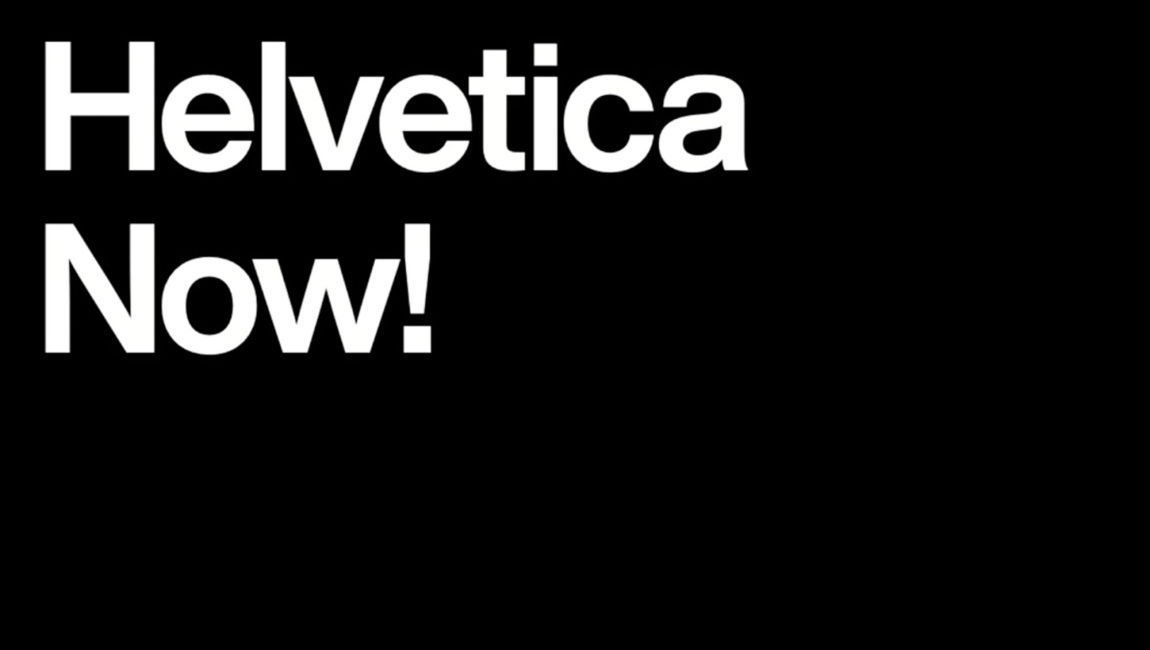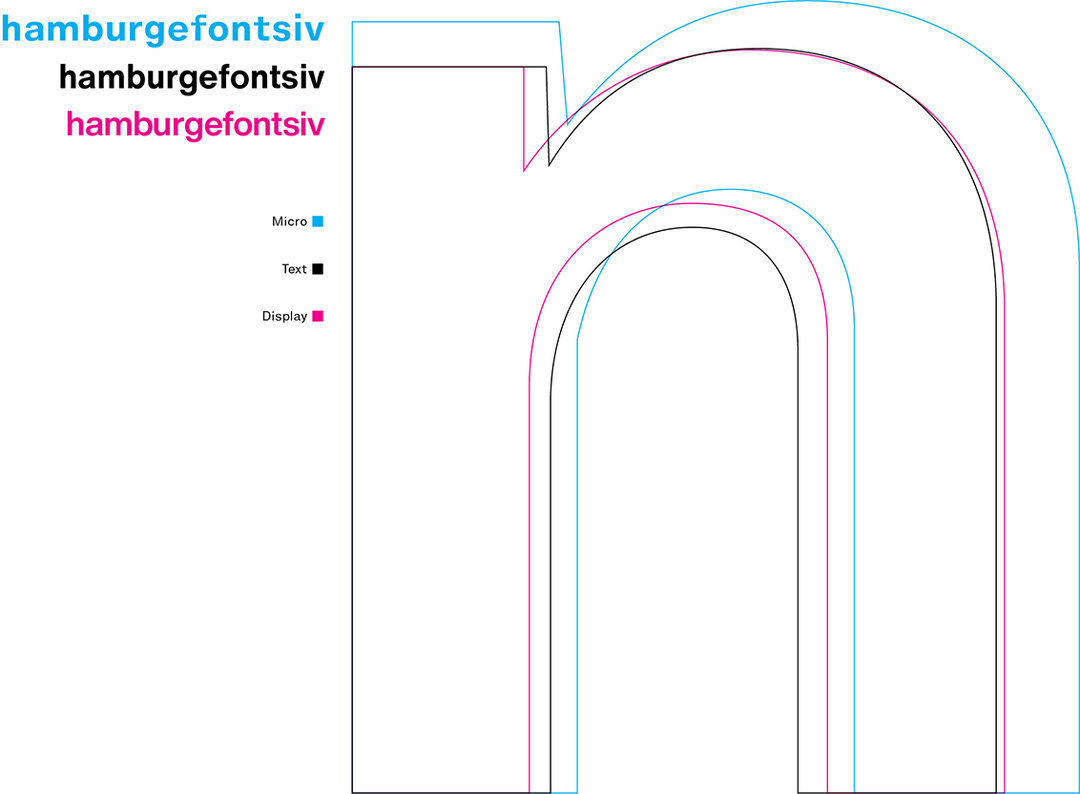
为了让经典的 Helvetica 字体更加适应当今时代,Monotype 公司经过多年的努力,终于在 Helvetica Neue 推出 35 年之后再次对 Helvetica 字体进行了更新,近日发布了全新版本的 Helvetica Now 字体。
Monotype 公司在声明中提到「Helvetica Now 是有史以来最著名字体的故事的新篇章。它提供了三种光学尺寸——微型、文本和显示。Helvetica Now 中的每个字符都经过重绘和重修,提供了更多种的选择。它拥有我们所喜爱的 Helvetica 字体的全部元素以及我们如今排版所需的一切。」
Helvetica 字体诞生于 1957 年,因便于识别、简单易读而被广泛采用并风靡全球。为适应时代需求,该字体于 1983 年经过重新设计后成为 Helvetica Neue 字体并延续至今。
苹果多年来一直也是 Helvetica 字体的拥护者,比如 iPhone 从初代开始就已将 Helvetica Neue 字体加入系统,并在 iOS 7 正式将其作为系统默认英文字体,而 Mac 从 Mac OS X 10.10 Yosemite 开始也将默认字体从之前的 Lucida Grande 改成了 Helvetica Neue。
不过由于科技的飞速发展,Helvetica 字体也在某些方面显得有些「落伍」,比如在小字体上的表现力偏弱。为了更好的适应 Apple Watch 的小屏幕,苹果自己研发了 San Francisco 字体,并在随后的 iOS 9 和 El Capitan 系统进行全平台推广,彻底取代了 Helvetica Neue。